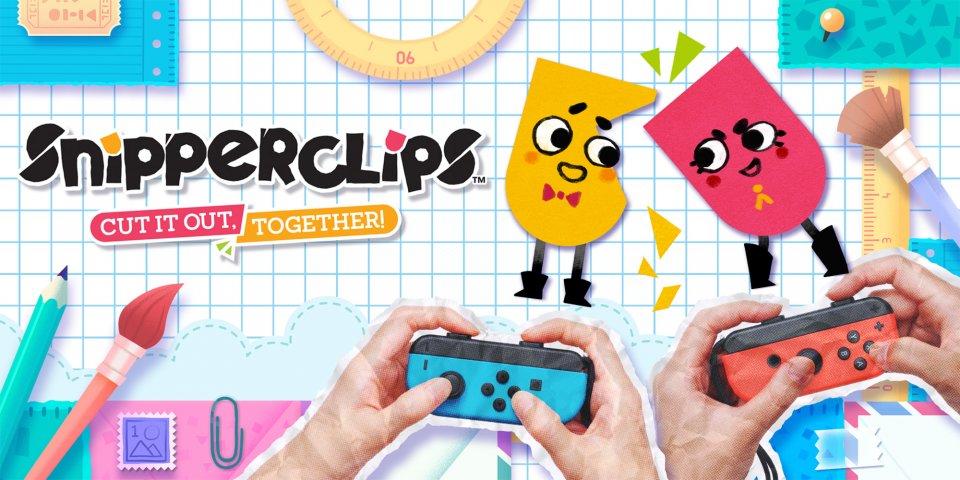
Wie heißt diese Schriftart? (Snipperclips)
suche die Schriftart aus dem Bild. Nur von "Snipperclips" nicht was darunter steht. Vielen Dank im Vorraus :)
Ich vermute, dass dieses Logo keiner Schrift entstammt sondern ein individuelles Werk eines Designers ist.
Ein Merkmal dafür ist z.B. das p: Das erste hat keine Ecke oben links, das zweite p schon.
Habe ich leider mit gerechnet, gibt es vielleicht eine ähnliche?
Was ist dir denn wichtiger? Das S oder die anderen Buchstaben?
Habe mich mal im WWW umgeschaut, jedoch entweder Fonts mit einem ähnlichen S oder eben den anderen Buchstaben gefunden. Zusammen wird es da nichts geben. :-?